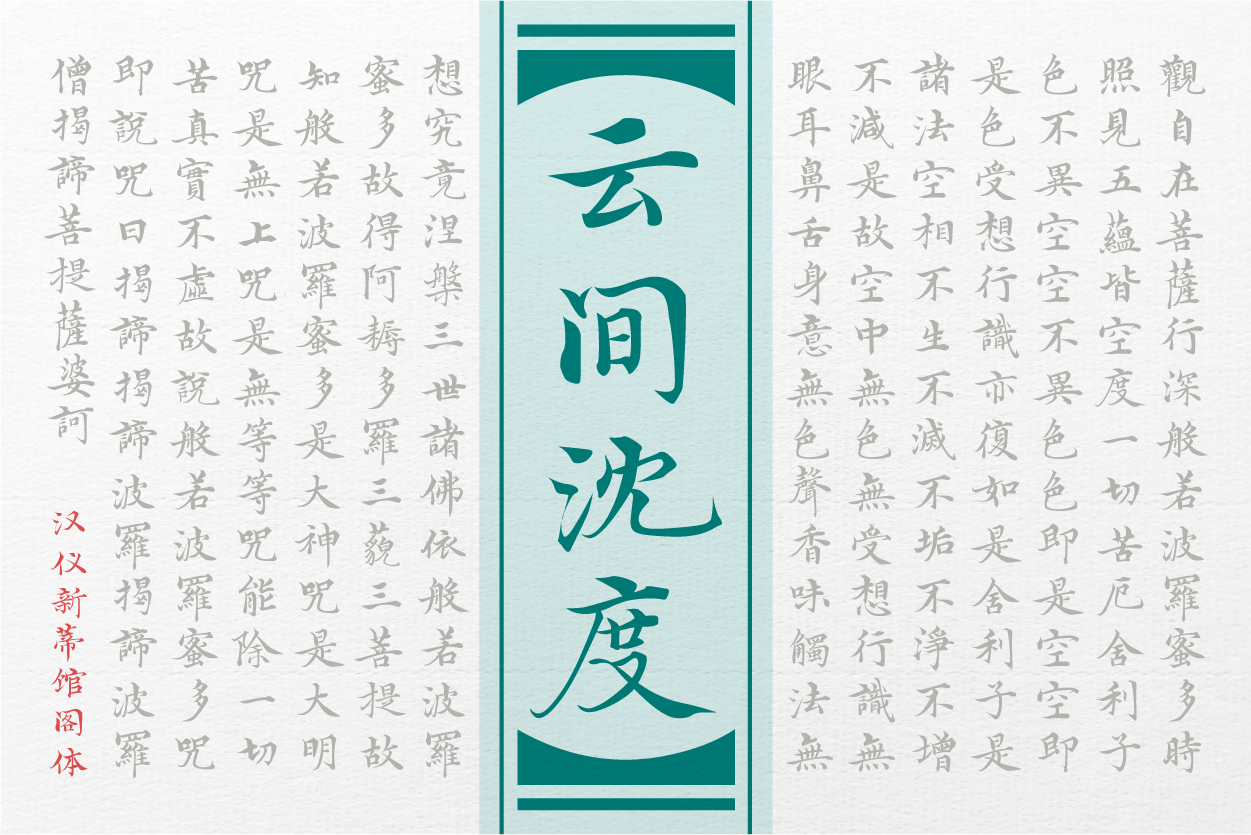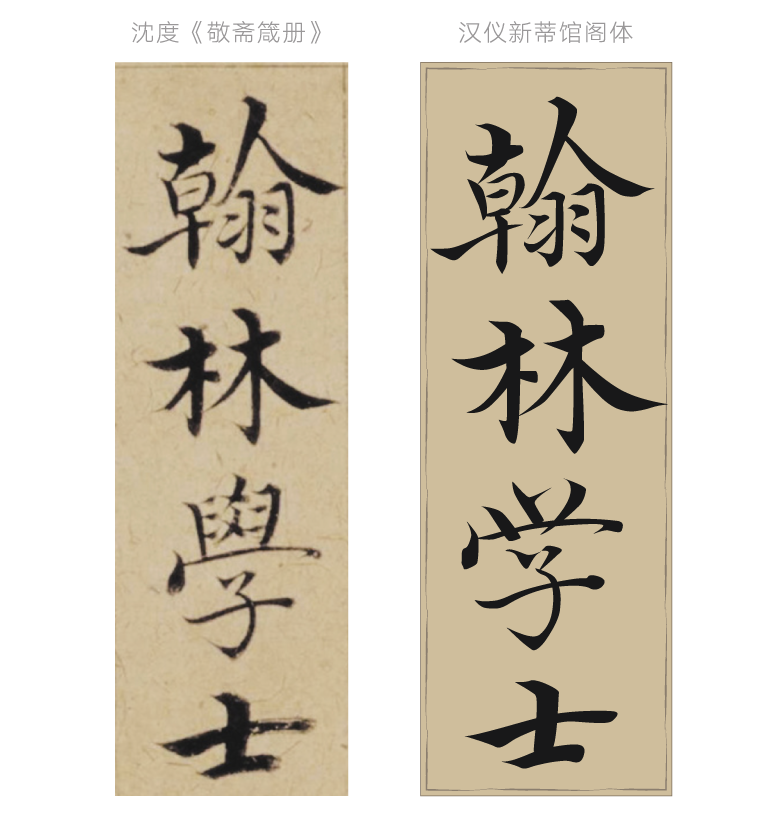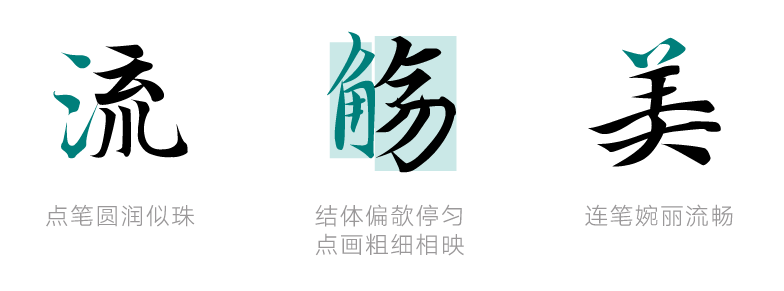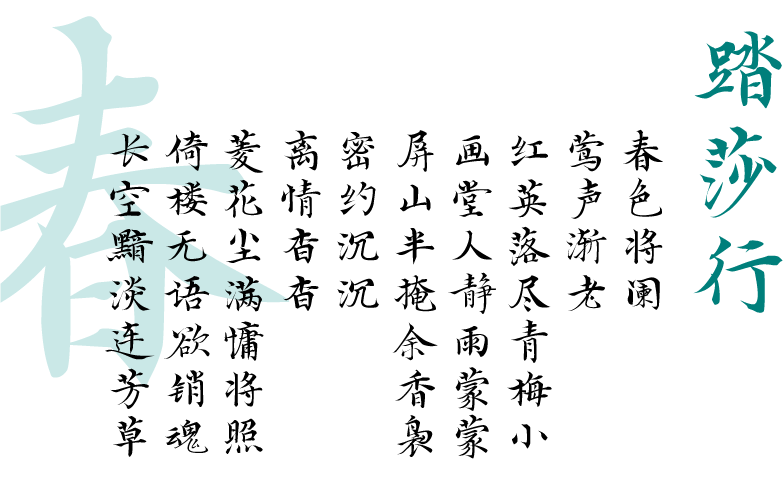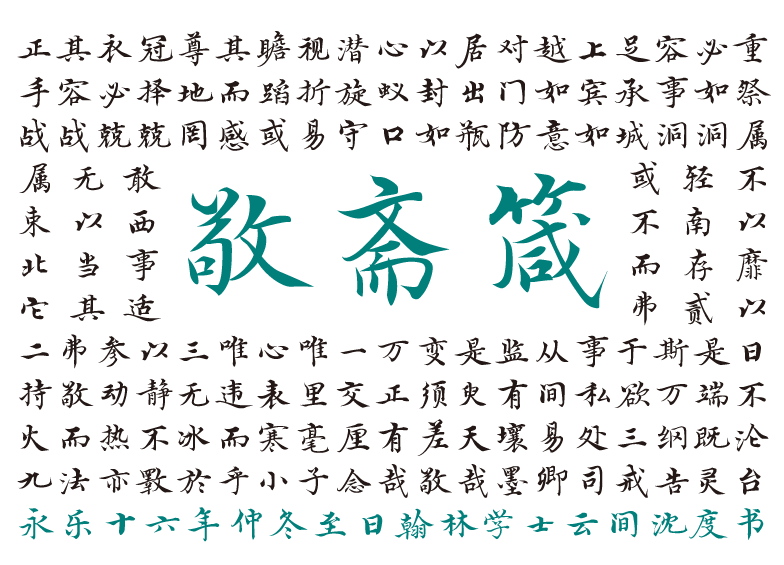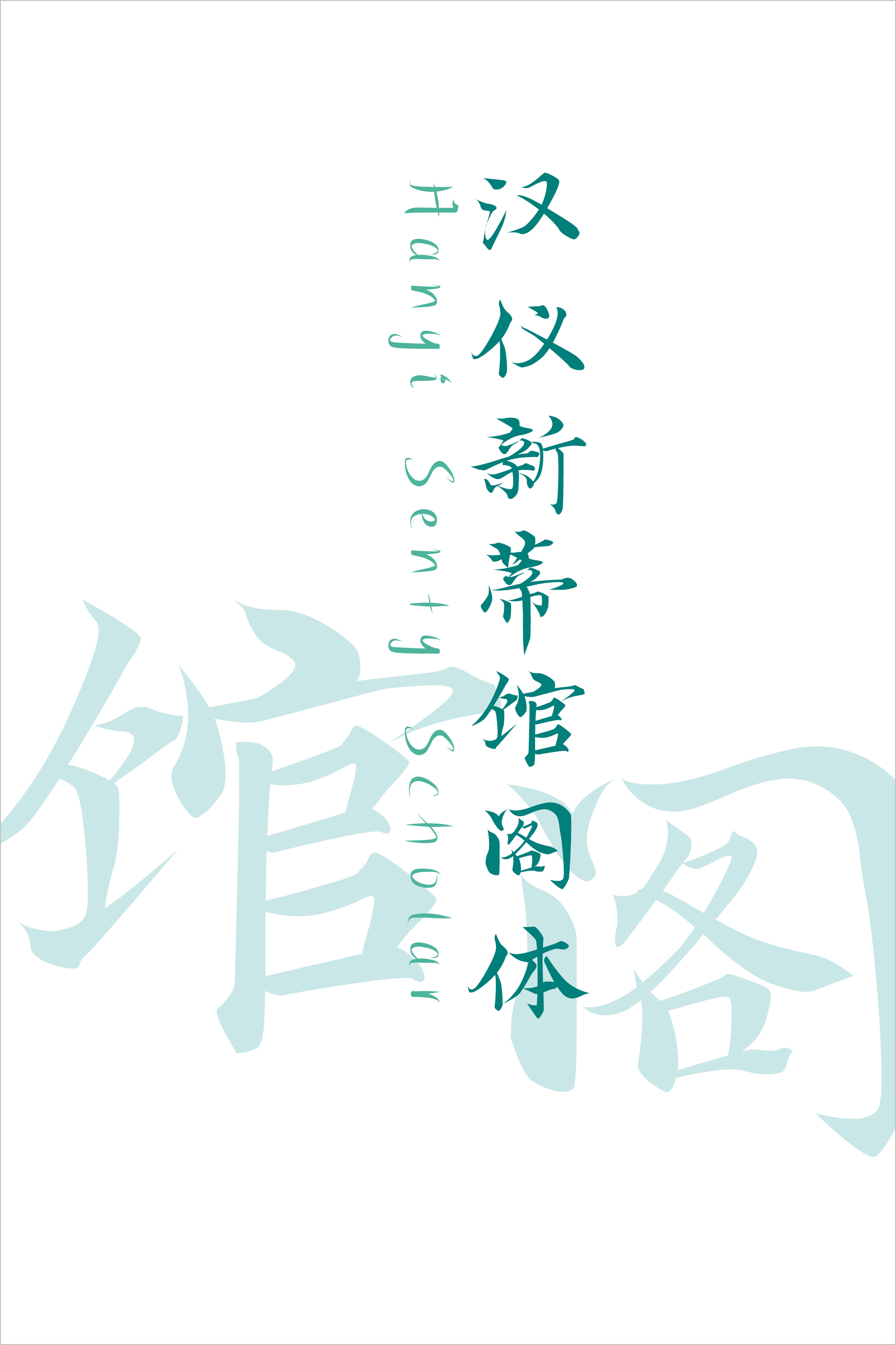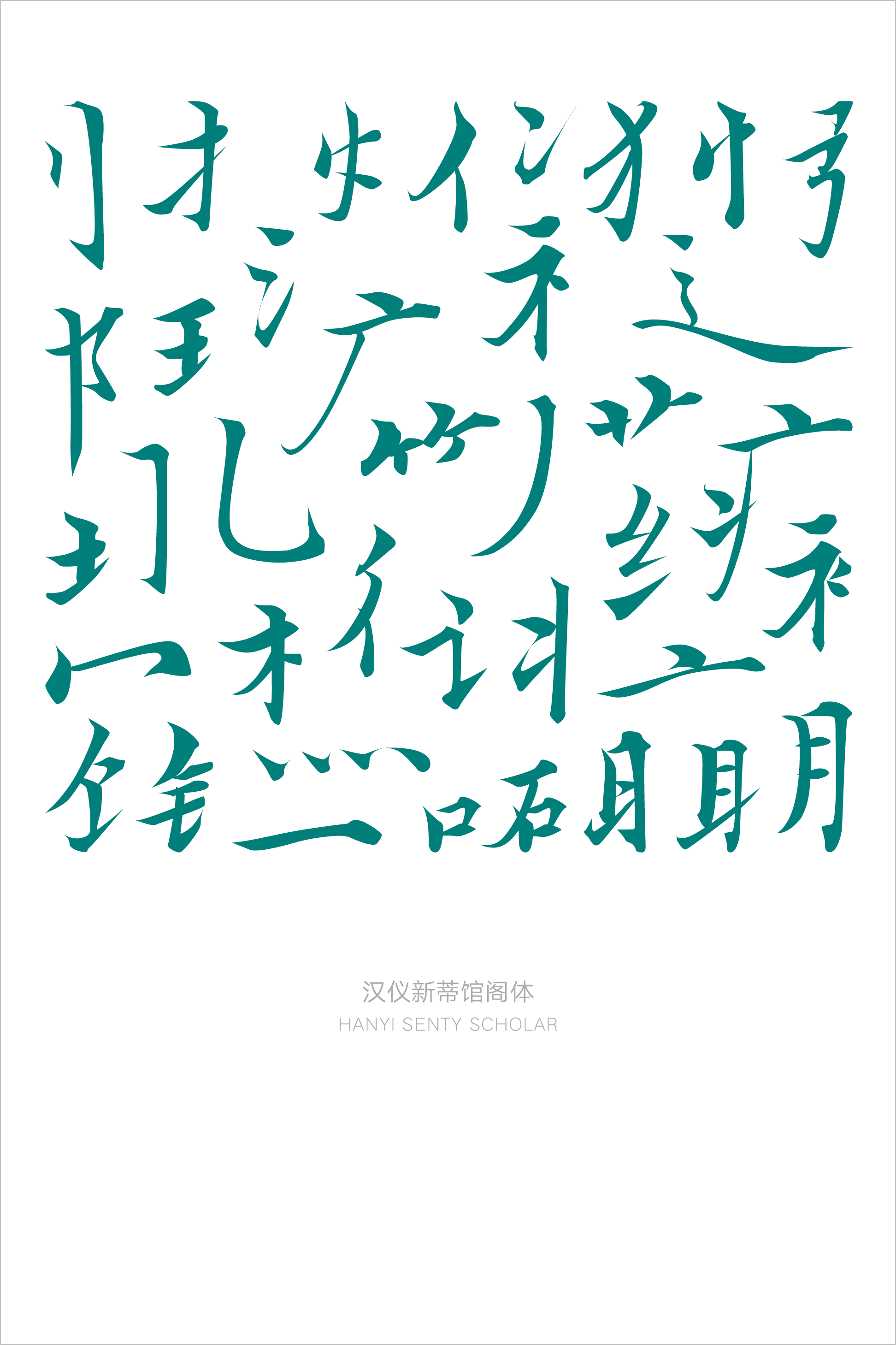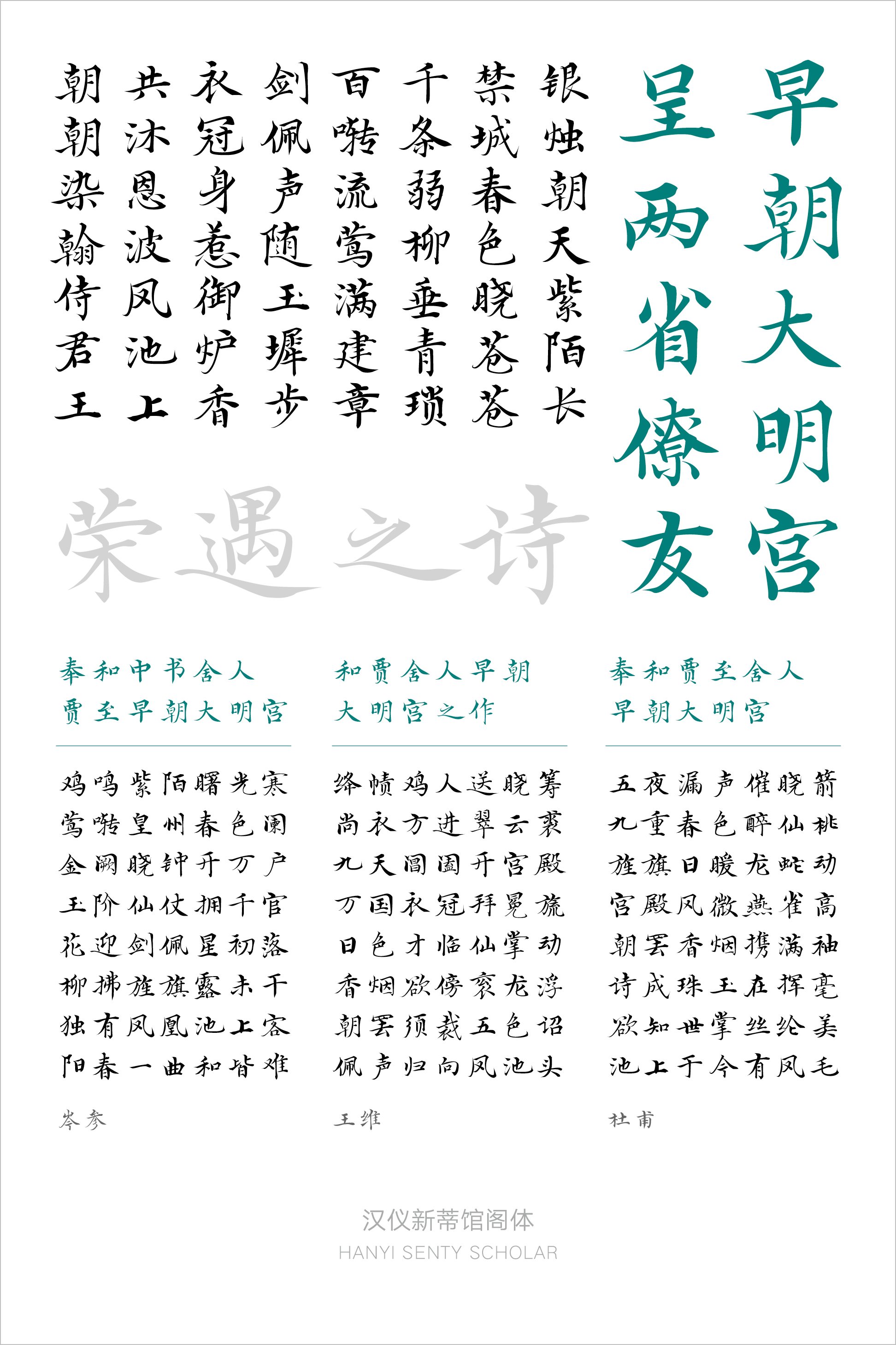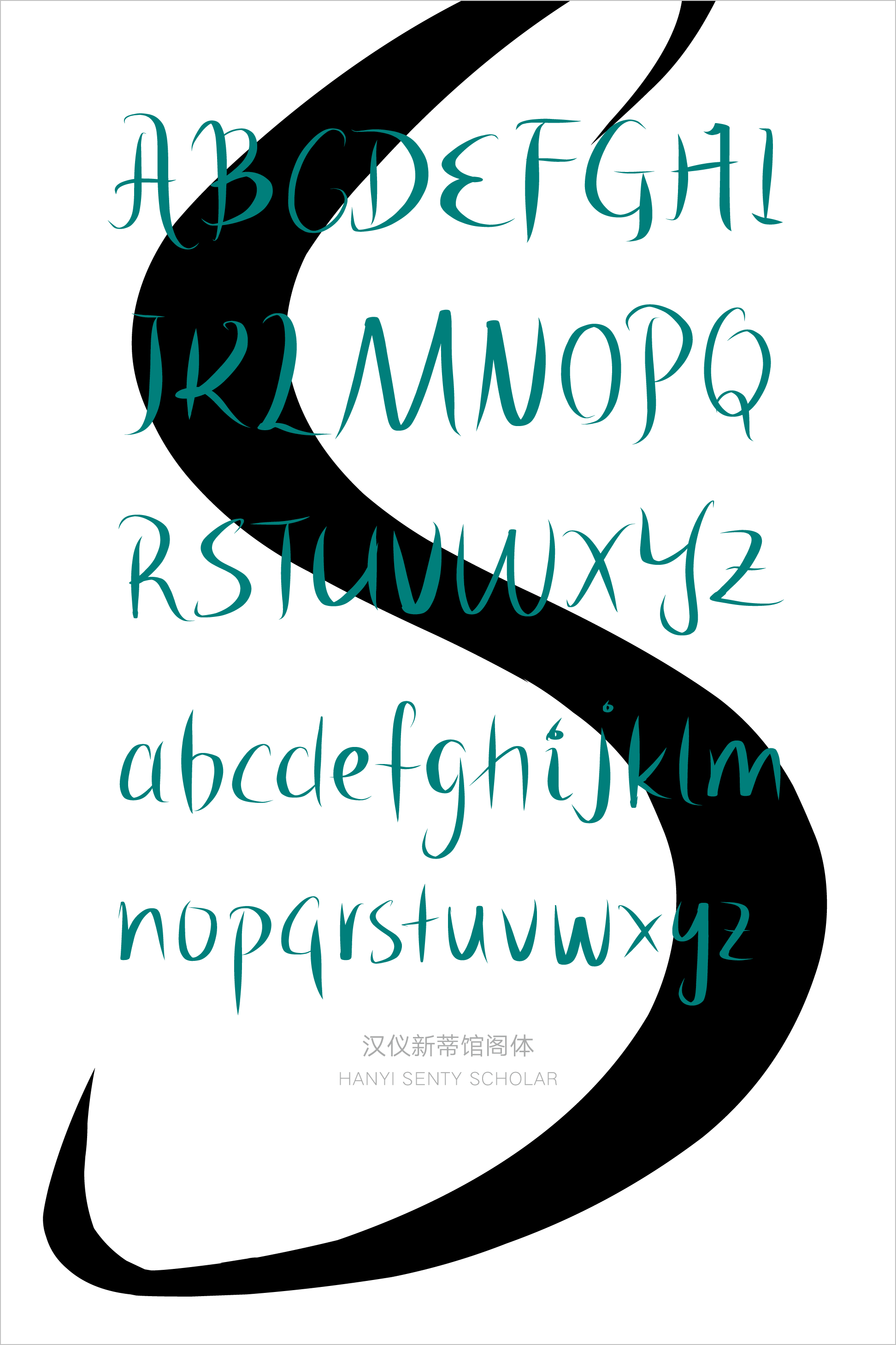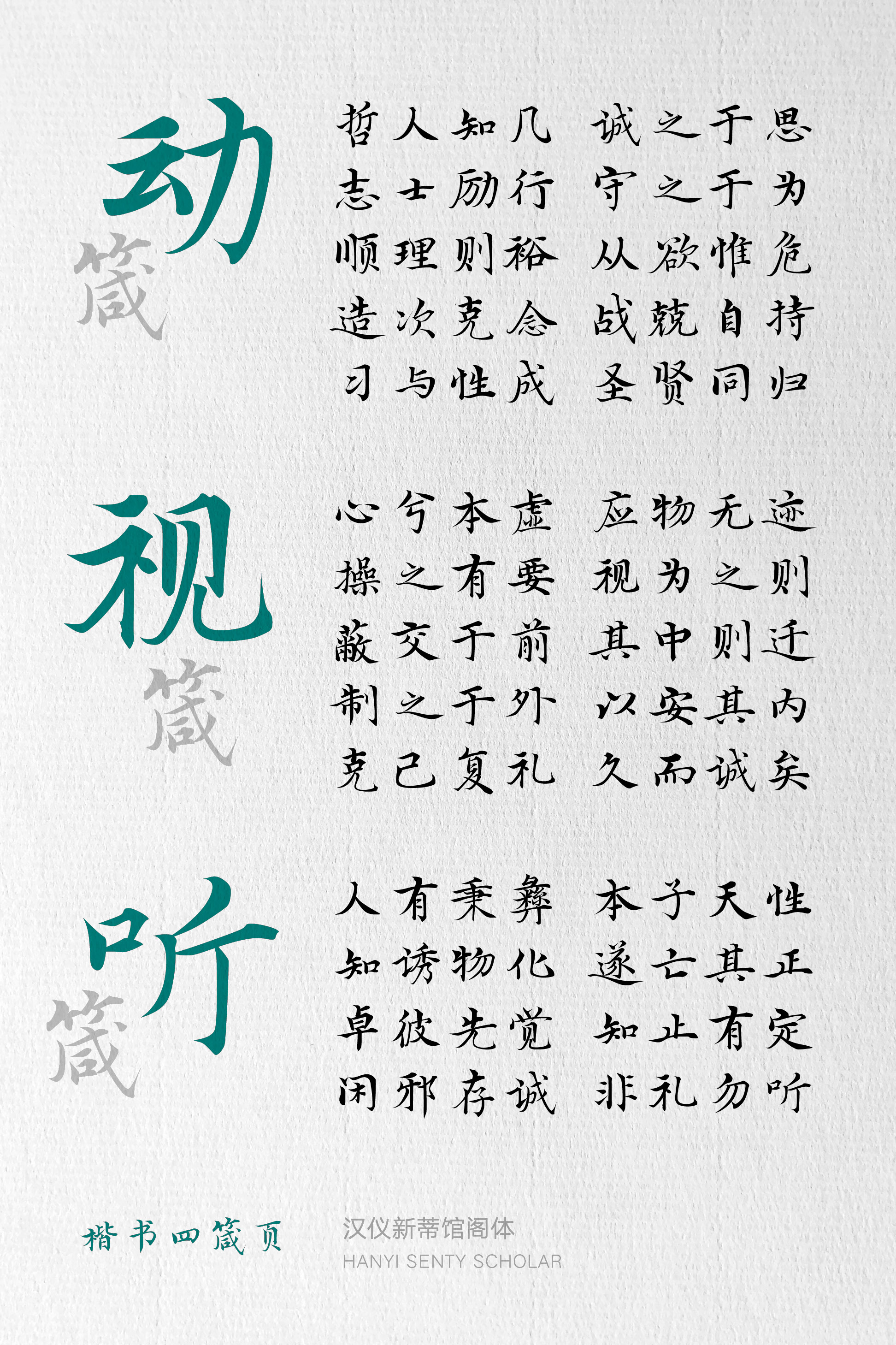
汉仪新蒂馆阁体字体介绍,汉仪新蒂馆阁体字体设计思路
古风 / 典雅 / 雍容 / 闲适
汉仪新蒂馆阁体是根据明代书法家沈度的存世小楷书法风格设计而成的,经过分析、临摹、学习其字形结构、运笔等,逐一设计制作了完整的常用字库。馆阁体演变至清代成为了官方文书和科举考试的标准字体。汉仪新蒂馆阁体在目前粗体大字盛行的字体环境下,为用户提供了一个清新儒雅、专注内敛的书法字体选择。
与一般大众印象中的馆阁体有所不同,汉仪新蒂馆阁体效法沈度书法作品,结体偏欹停匀、婉丽端庄,可为版面增添一种雍容祥和的庙堂气象。
该字体笔笔工致稳健、体态珠圆玉润,点画粗不为重、细不为轻,法度俱存、中规入矩,给人一种婉丽端妍的感觉。